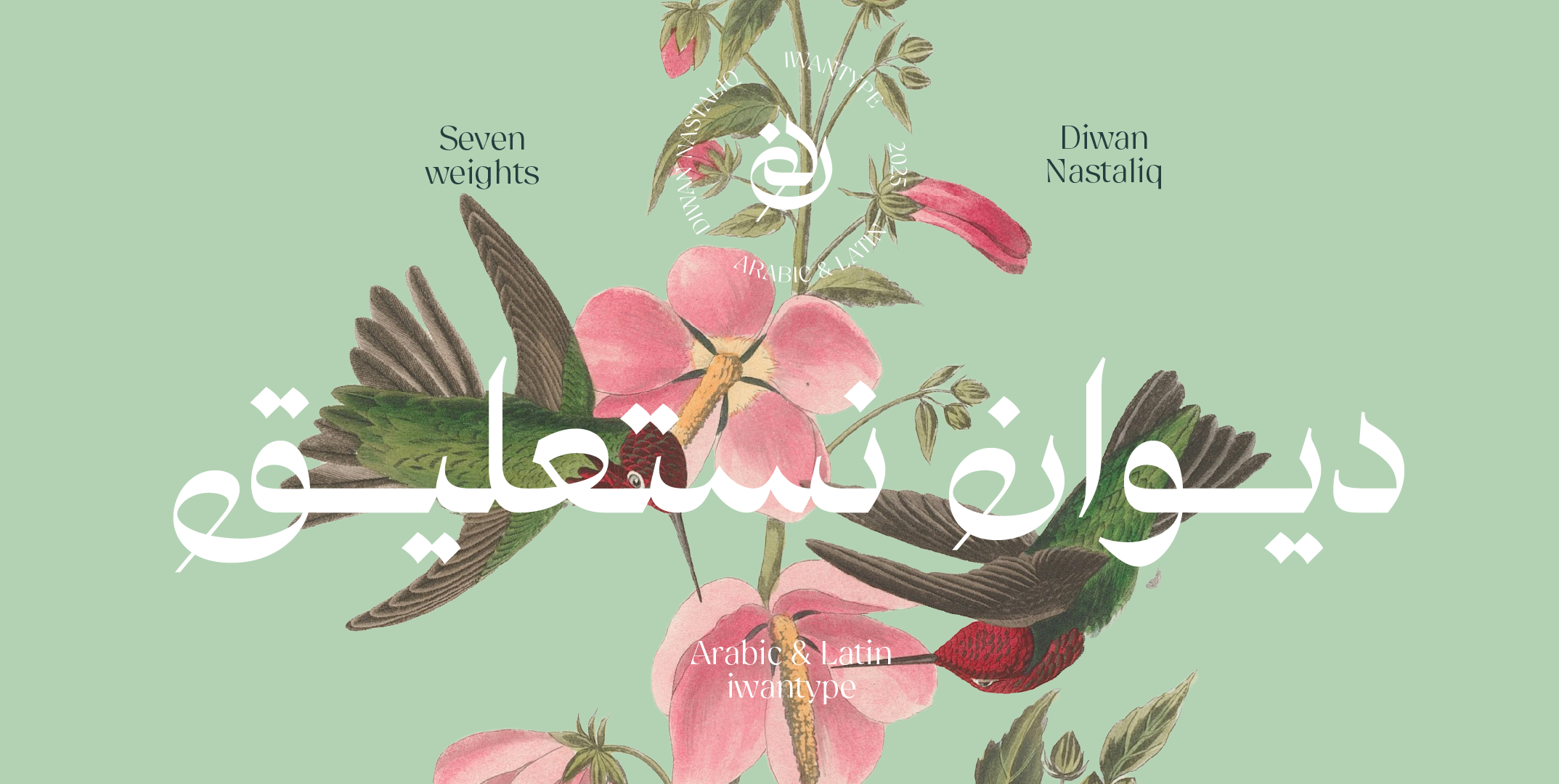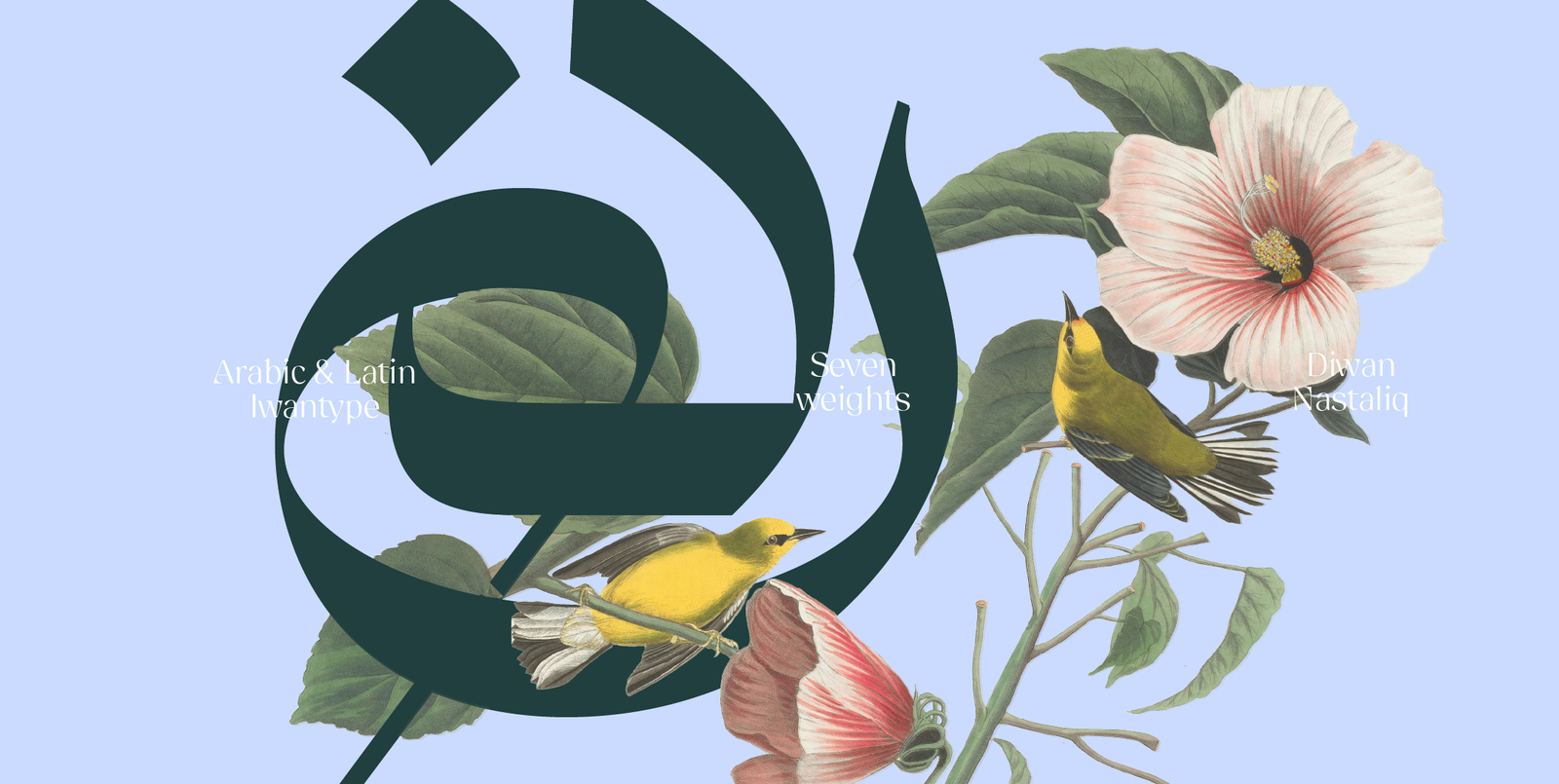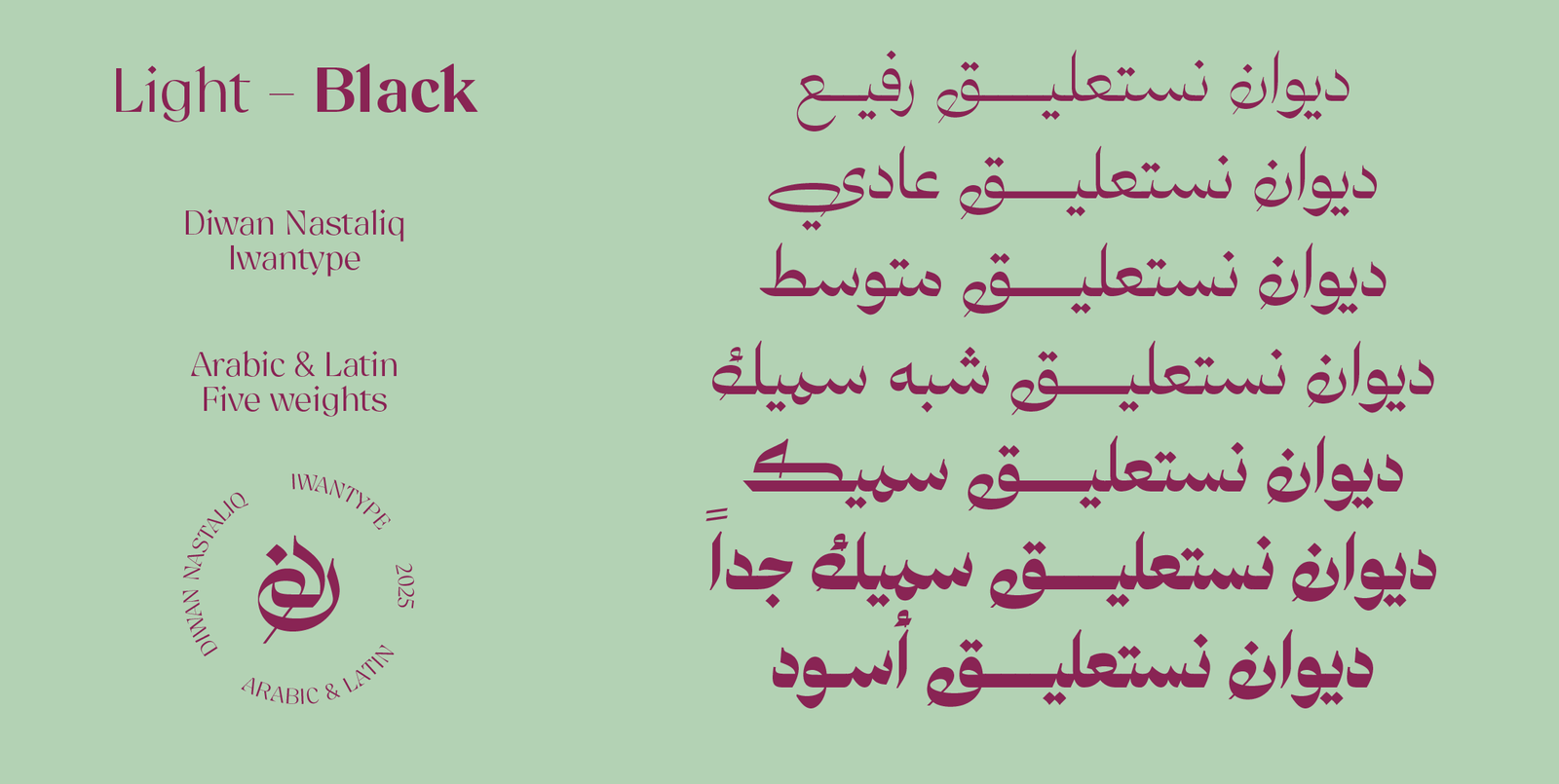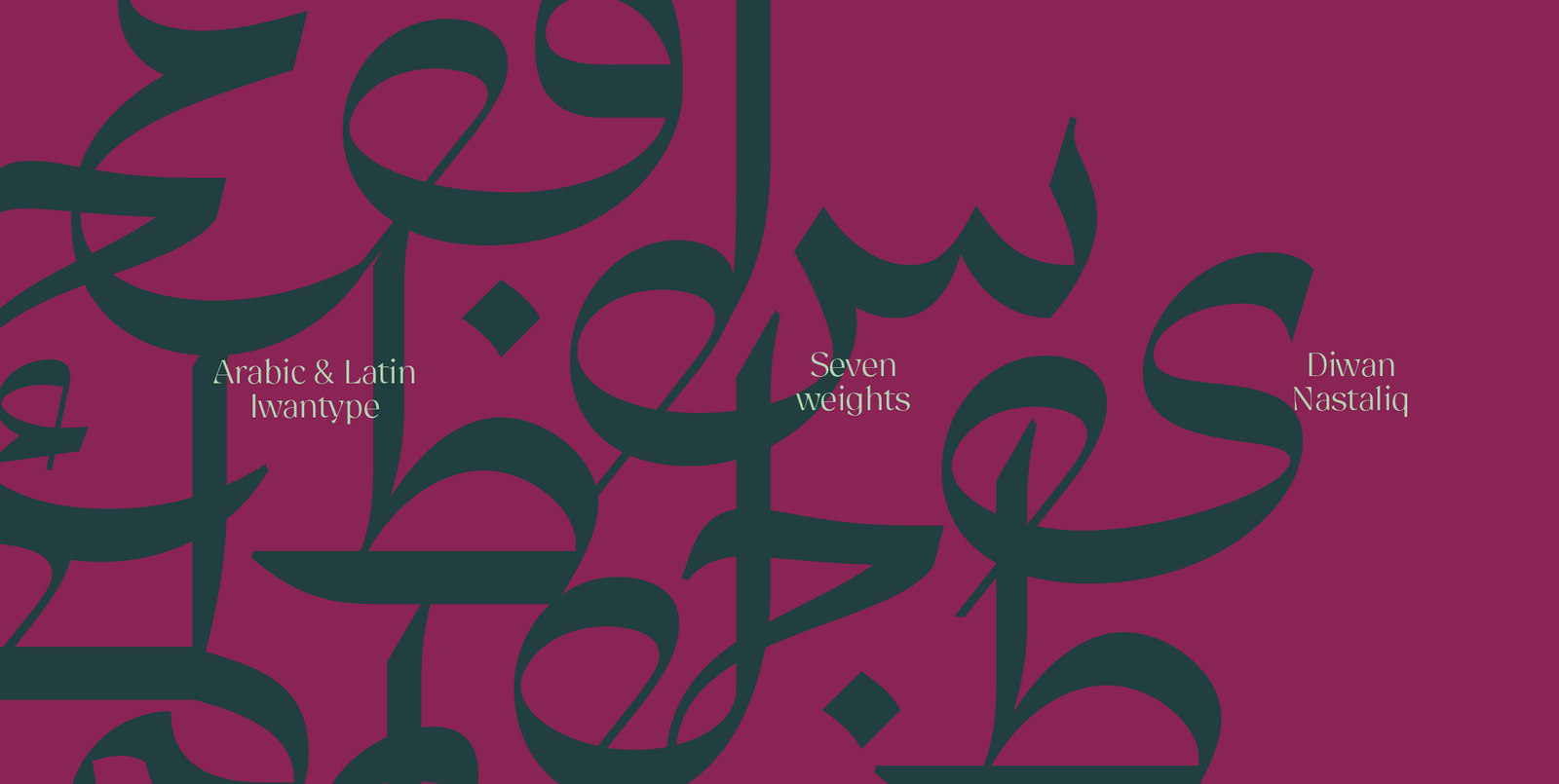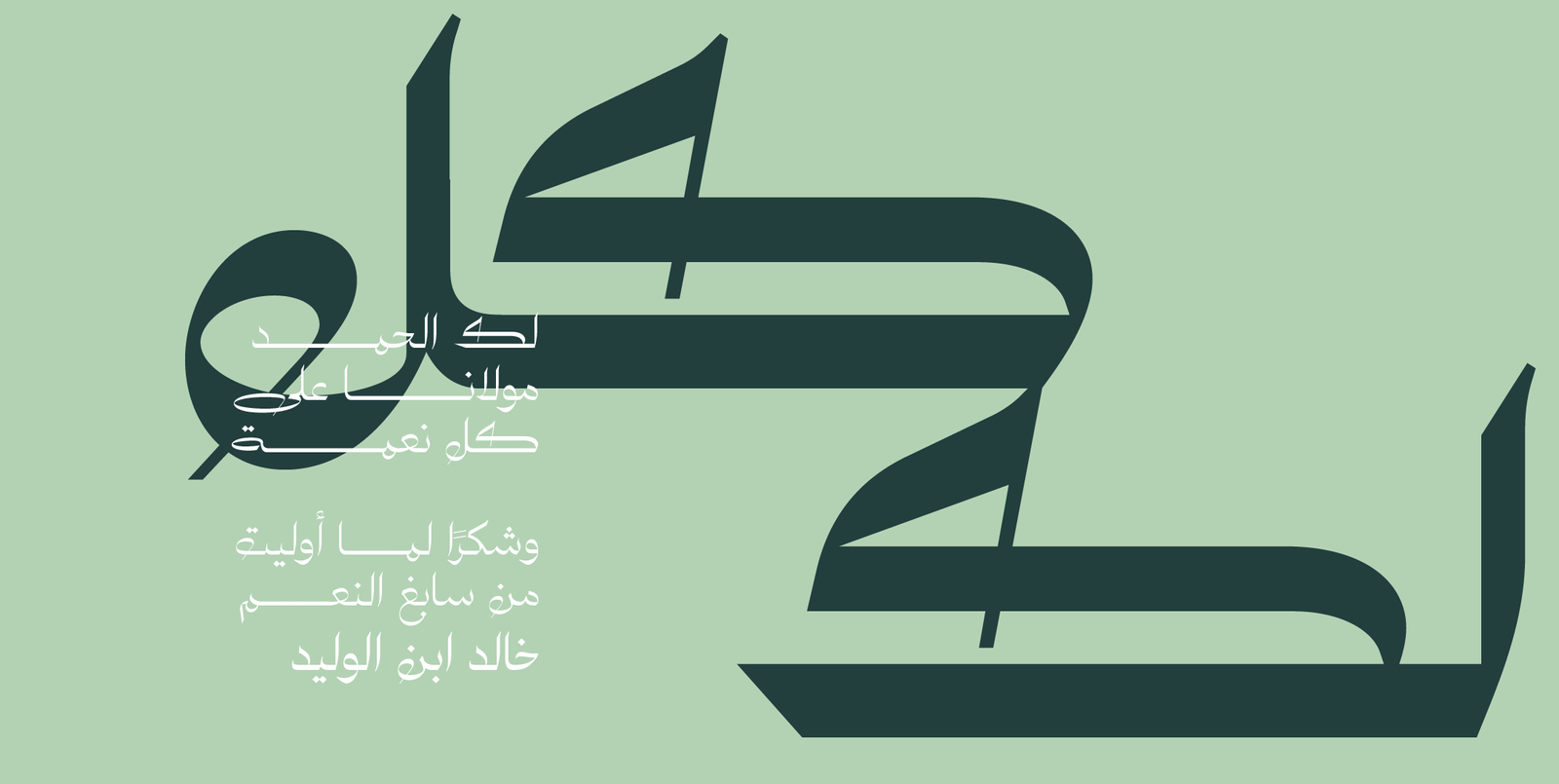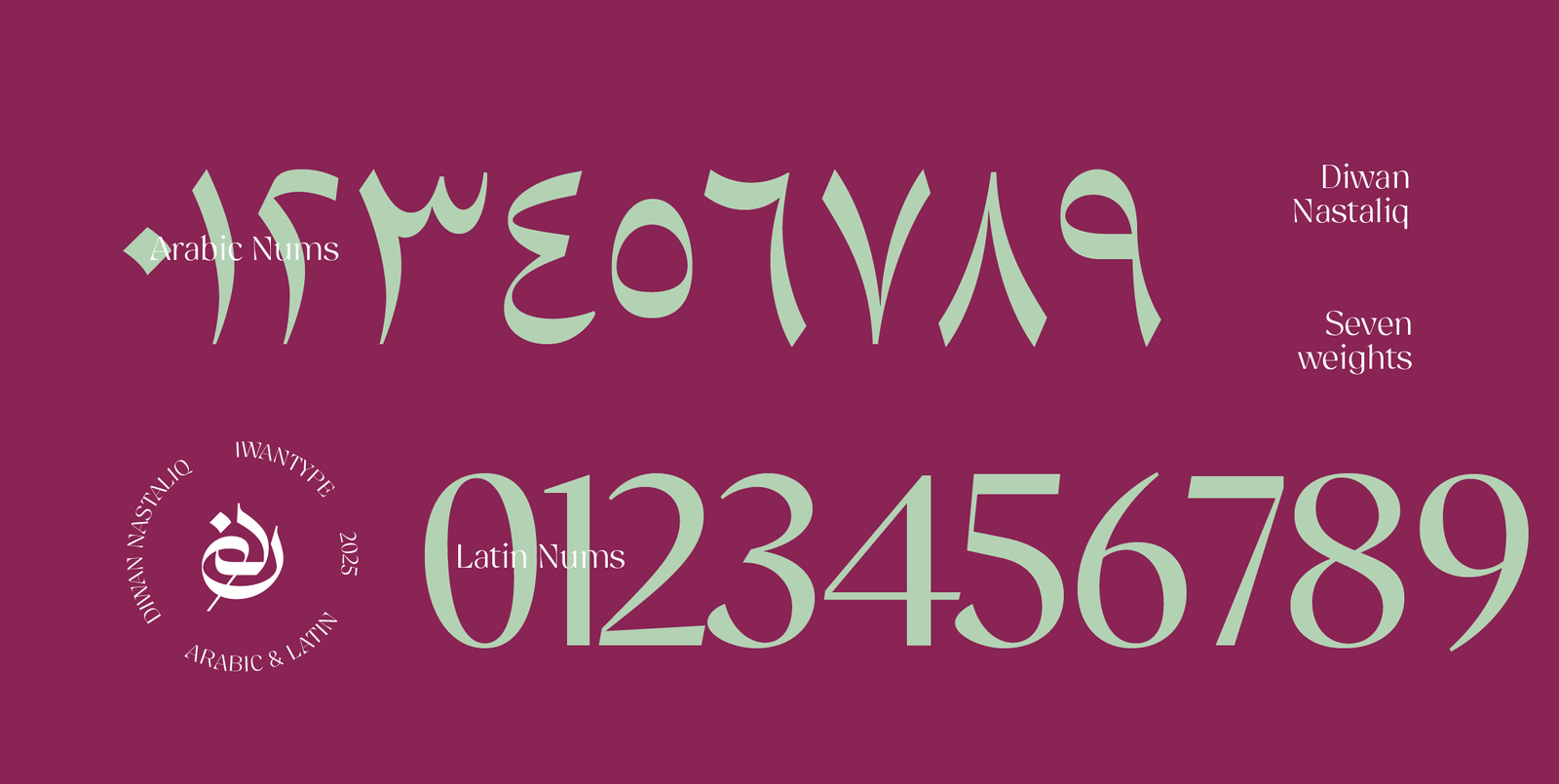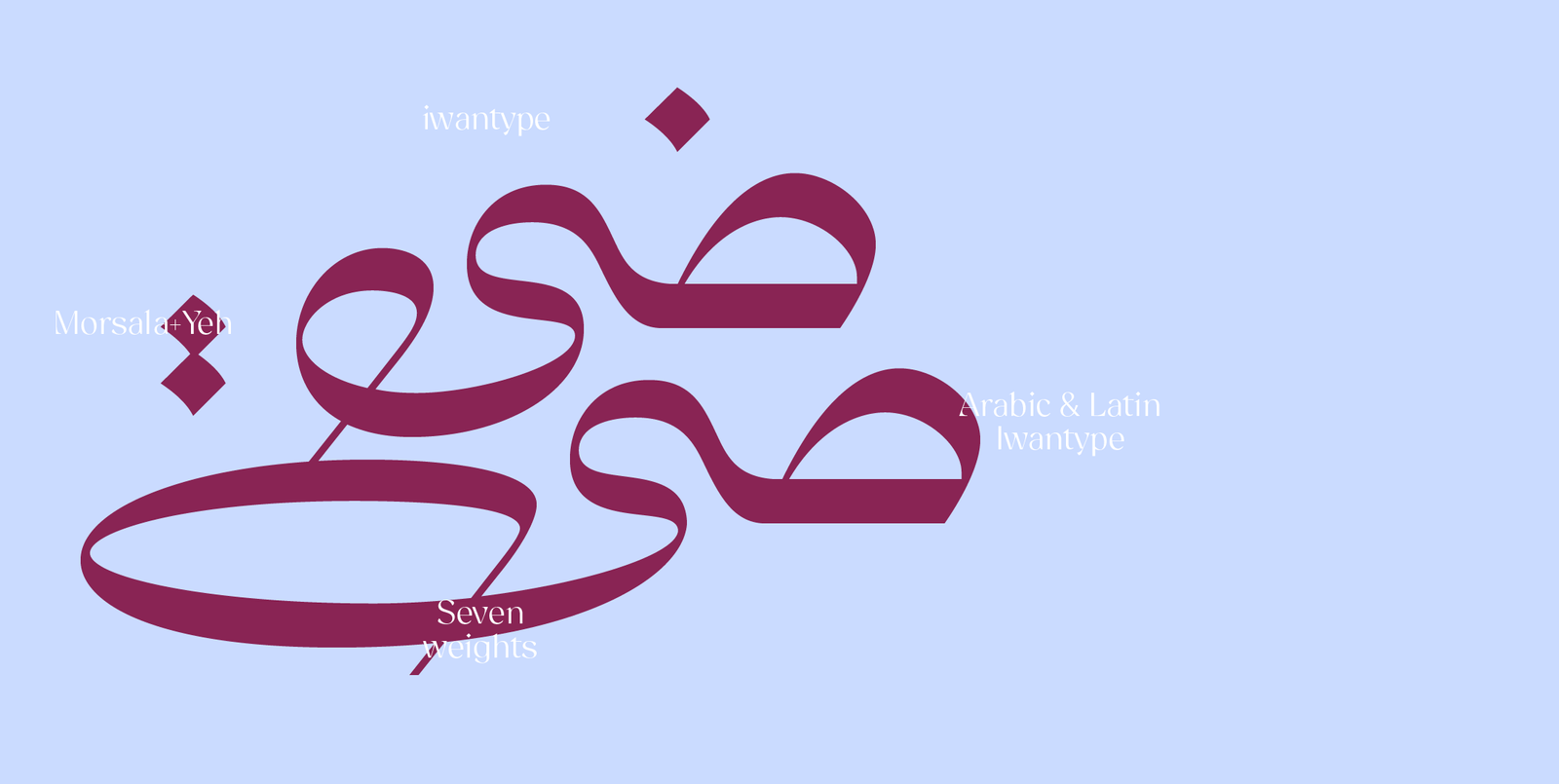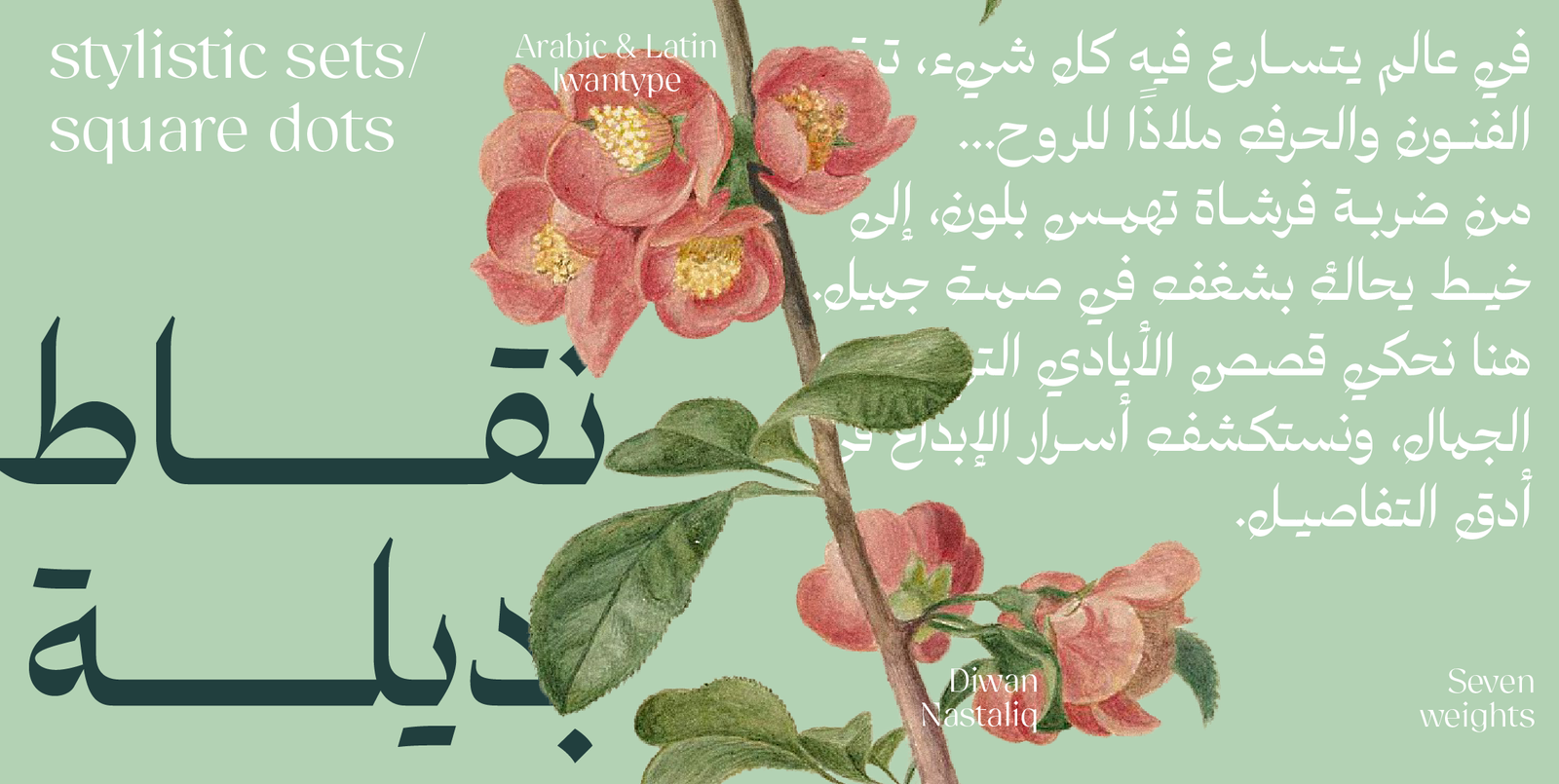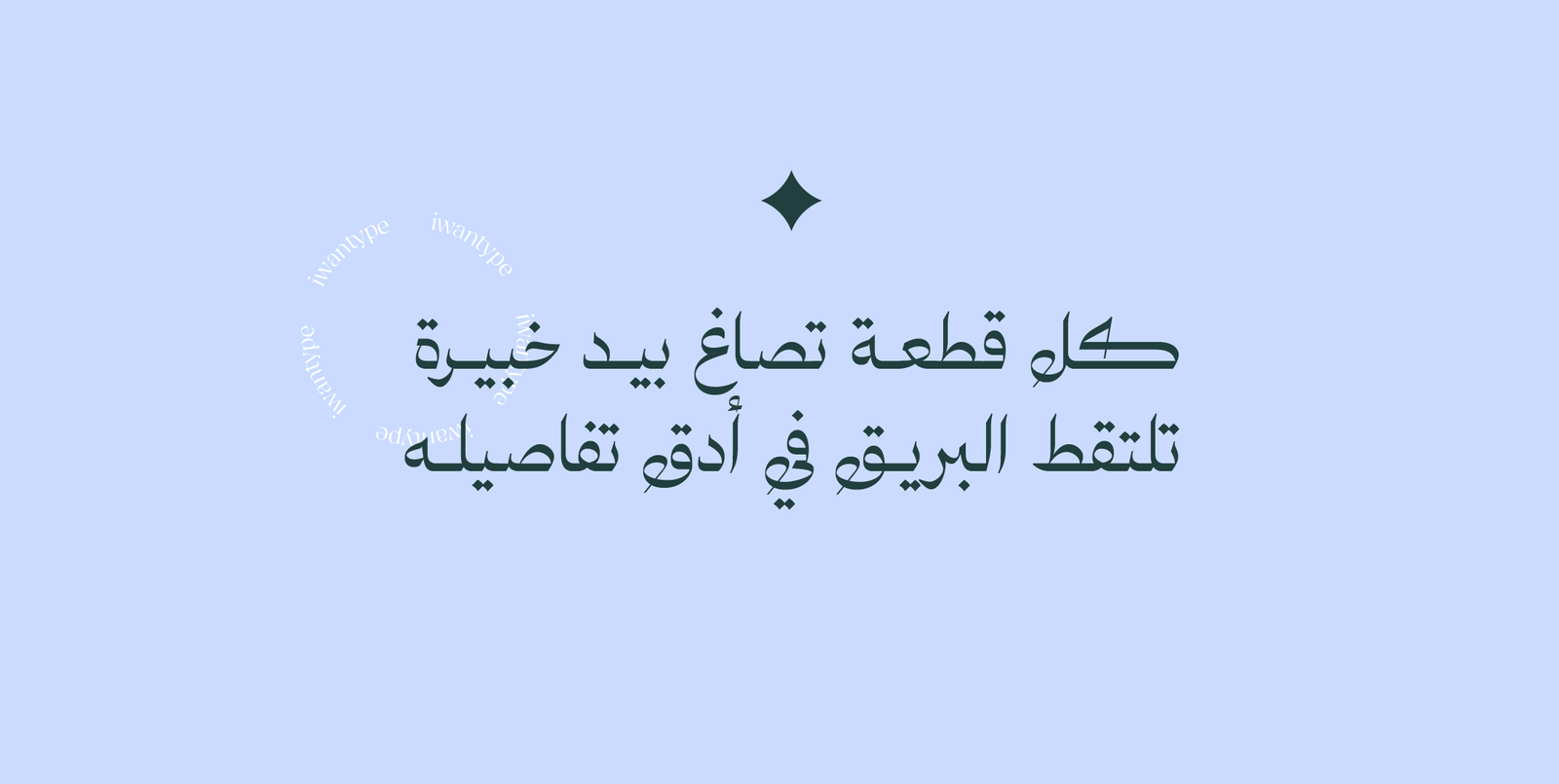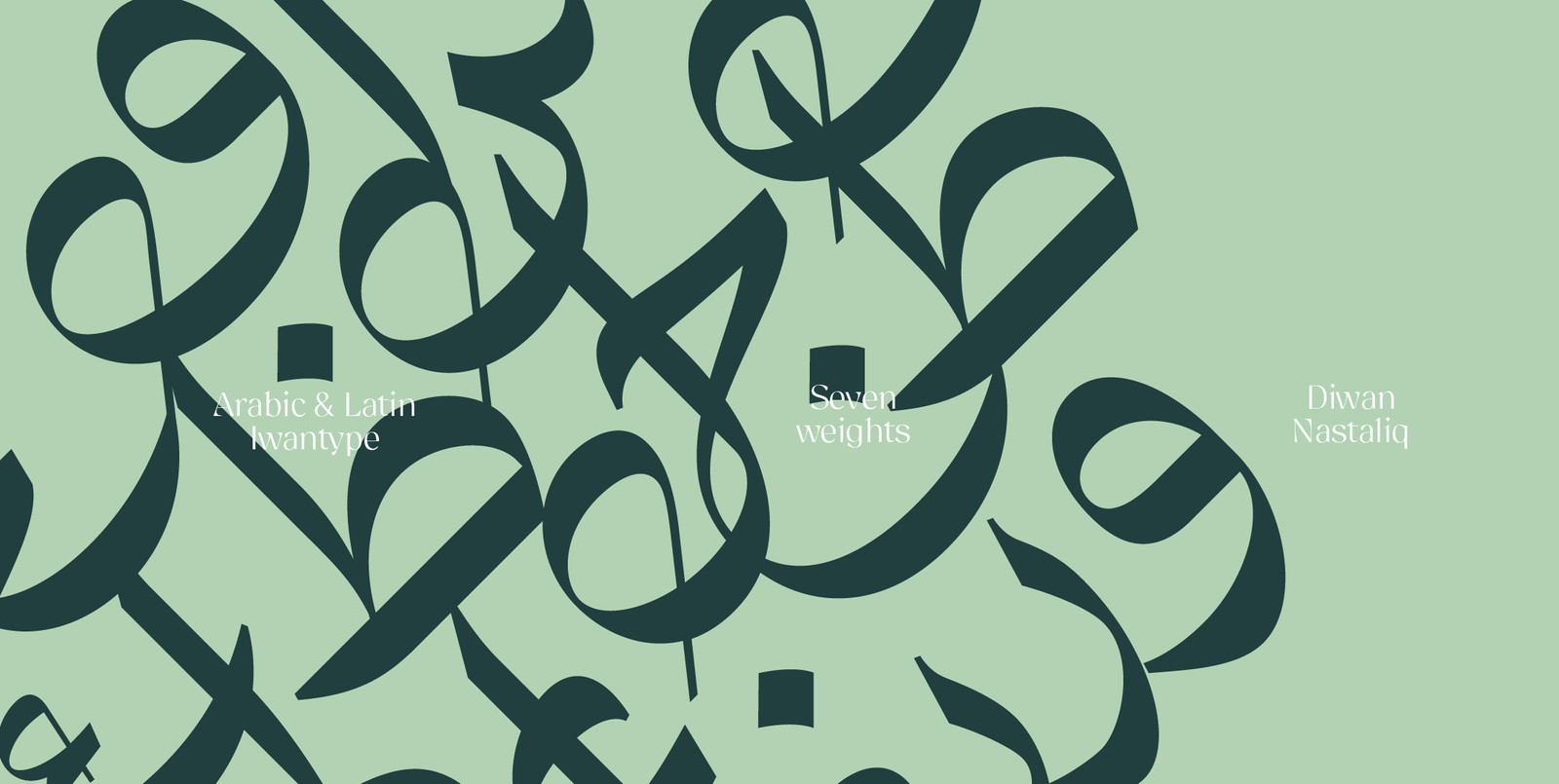
خط ديوان نستعليق Diwan Nastaliq
ديوان نستعليق Diwan Nastaliq — همسٌ بصريّ ينساب برفاهية
يأتي ديوان نستعليق الإصدار الثاني من خط ديوان كطبقة ناعمة من الحبر تنساب فوق قماش قطني هادئ، يترك أثره بخفةٍ تشبه التنفّس.
تتدرّج أوزانه السبعة من الرفيع الذي يشبه خيط ضوء، إلى الأسود الذي يمنح الكلمة ثقلًا مخمليًا يليق بعلامة تبحث عن حضور راقٍ ومتّزن. وبينهما، يعيش الخط في مساحات واسعة من الهدوء البصري والرفاهية الناعمة.
مناسب للعناوين الراقية، للهويات التي تحب الصمت الأنيق، وللمصممين الذين يختارون الحرف بقلوبهم قبل أعينهم.
مميزات خط ديوان نستعليق:
يتضمن الخط العديد من مزايا OpenType التي تضفي عليه مرونة وتنوعًا في الاستخدام، مثل:
- أحرف مرسلة (تُفعَّل بإضافة “ءء” بعد الحرف)
- حرف ياء بنزول أقل: يقلل من نزول السطر، مما يعزز من انتظام النصوص.
- أحرف المركبة: تسهم في تحسين المظهر العام للنص وتزيد من سلاسته.
- نقاط بديلة
- يدعم رمز الريال السعودي، ويمكن تفعيله بإضافة حرف “ء” بعد كتابة كلمة “ريال”.